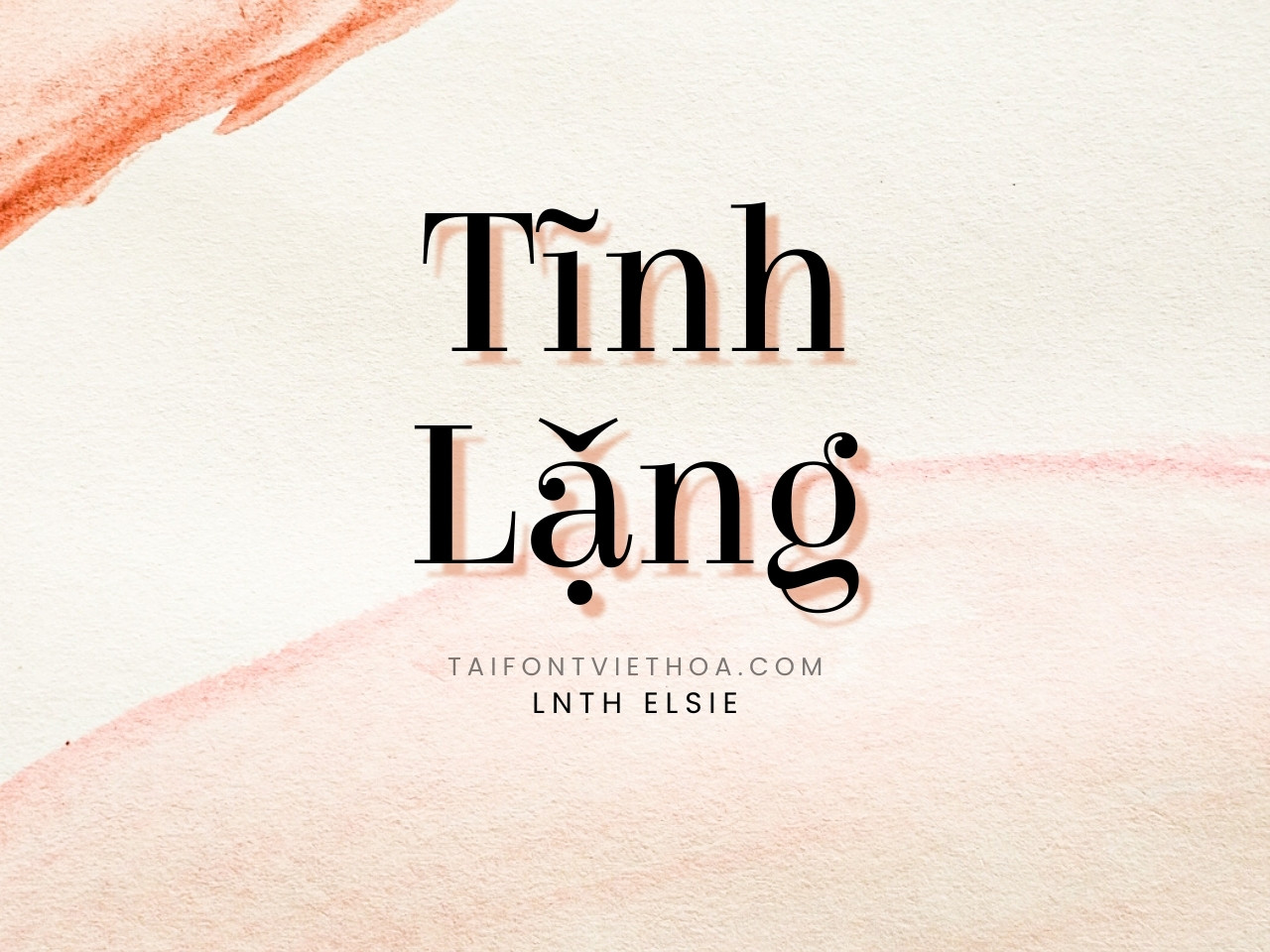
Font việt hóa LNTH Elsie
Giới thiệu về font LNTH Elsie – Thanh lịch, cổ điển và nữ tính đầy tinh tế
LNTH Elsie là phiên bản Việt hóa từ font gốc “Elsie” – một phông chữ serif trang nhã được phát triển bởi Alejandro Inler dành riêng cho Google Fonts. Font được thiết kế để tôn vinh vẻ đẹp cổ điển của phụ nữ, mang cảm hứng từ thời kỳ Victorian kết hợp yếu tố hiện đại. Với cấu trúc serif mềm mại, đường nét tinh tế và các chi tiết cong đầy nữ tính, Elsie là lựa chọn hoàn hảo cho các dự án cần yếu tố sang trọng và duyên dáng. Phiên bản Việt hóa được thực hiện bởi Tuỳn Pucca, hỗ trợ đầy đủ tiếng Việt cùng hơn 60 ngôn ngữ khác, sẵn sàng phục vụ mọi nhu cầu thiết kế đa quốc gia.
Font này đã được taifontviethoa.com tuyển chọn và giới thiệu như một lựa chọn lý tưởng cho các dự án branding mỹ phẩm, blog thời trang, thiệp mời cưới hay ấn phẩm in ấn trang trọng. LNTH Elsie mang đến một phong cách cổ điển, quý phái nhưng vẫn dễ ứng dụng trong các thiết kế đương đại, tạo nên điểm nhấn đầy thẩm mỹ trong giao diện thị giác.
Đặc điểm thiết kế và ứng dụng nổi bật của LNTH Elsie
LNTH Elsie là kiểu serif cách điệu với độ dày – mảnh xen kẽ hợp lý, tạo nên độ tương phản cao giúp văn bản nổi bật và dễ đọc. Các nét cong và chân chữ được xử lý mềm mại, gợi cảm giác quý phái và cổ điển. Phông chữ này phù hợp để làm tiêu đề, logo, bao bì sản phẩm hoặc bất kỳ thiết kế nào cần một cảm giác tinh tế và đậm chất nữ tính.
Ứng dụng nổi bật: bộ nhận diện thương hiệu mỹ phẩm cao cấp, poster thời trang, thiệp cưới, bìa sách hoặc blog dành cho phụ nữ. Ngành nghề phù hợp gồm: làm đẹp, thời trang, sự kiện, giáo dục sáng tạo và ngành hàng cao cấp. Đây là font chữ có thể đồng hành lâu dài cùng các thương hiệu hướng đến sự thanh lịch và phong cách cổ điển hiện đại.